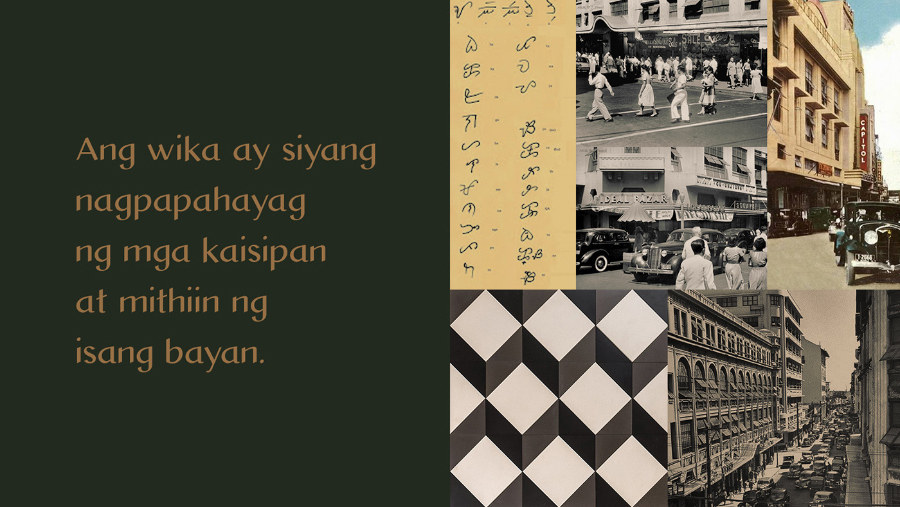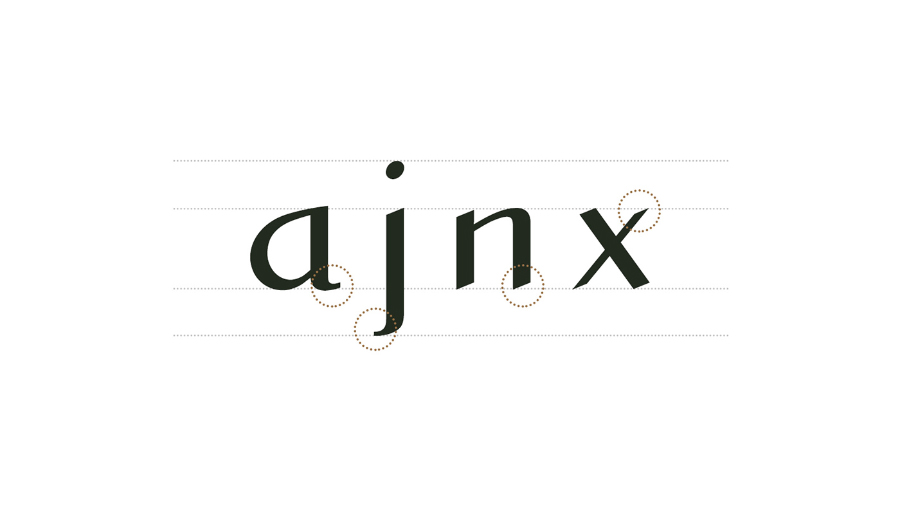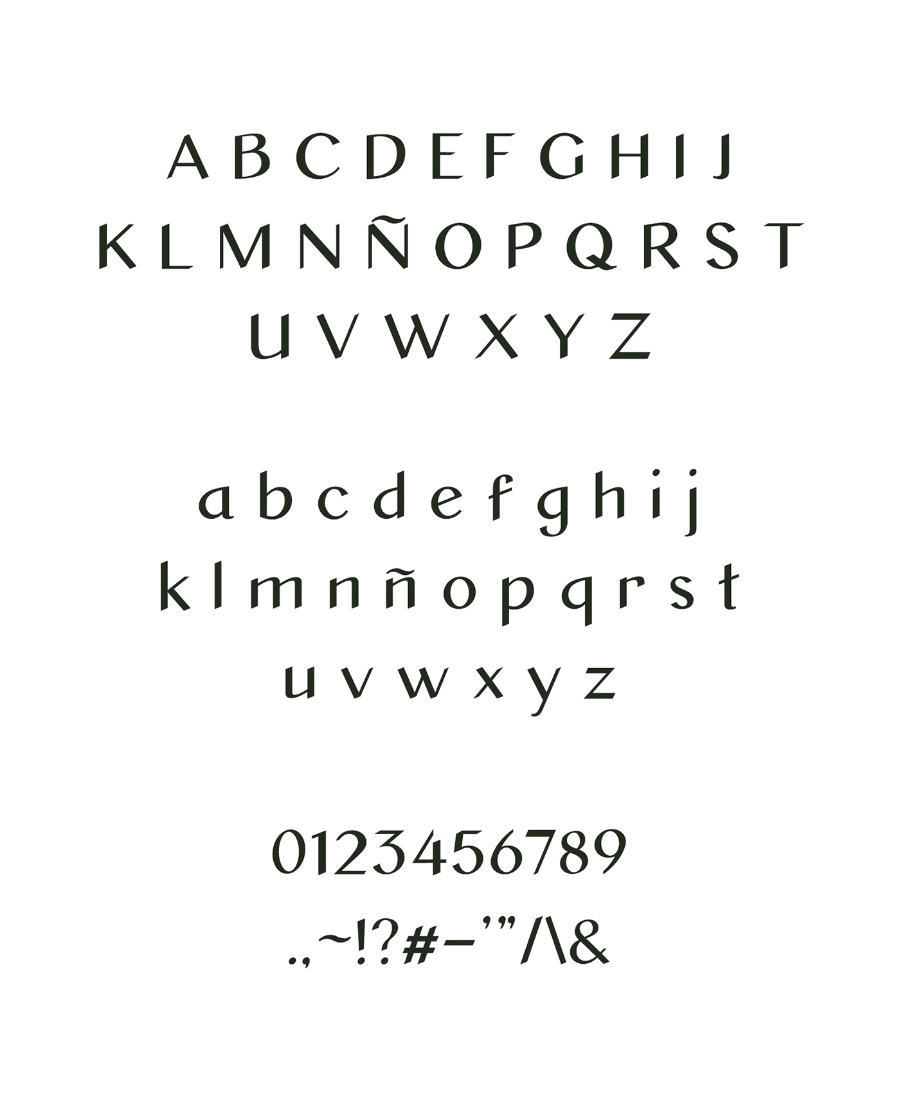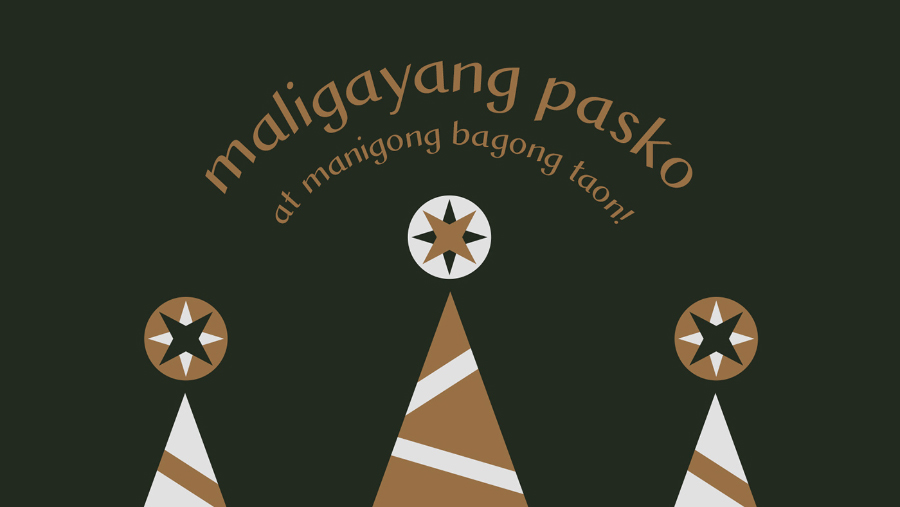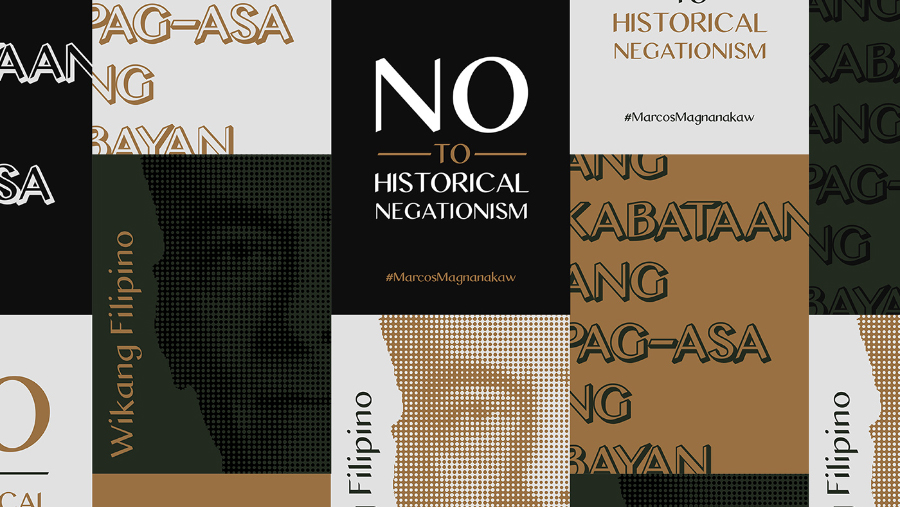
奎松免费免费字体
Quezon Sans Free字体是以“菲律宾语之父”命名的人文主义字体。这个城市也是笔者泡菜李长大的地方。受到装饰艺术,古代菲律宾文字“Baybayin”和马尼拉大都会旧建筑物的混合的启发,今天仍然站立。字体具有锐利的斜线,优雅平缓的斜坡。奎松将使它在企业标志,标题和品牌方面也是完美的。